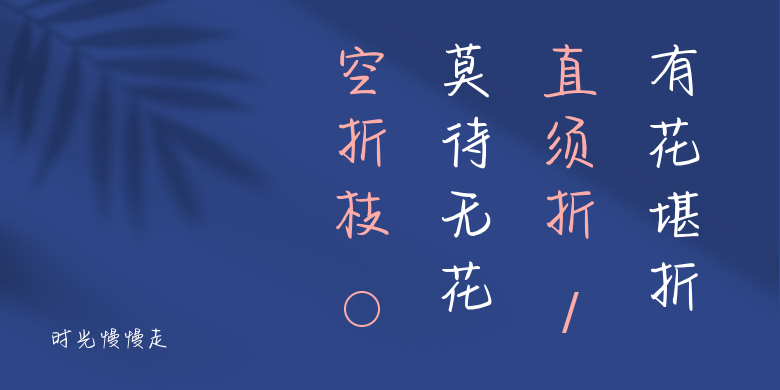
时光慢慢走
时光慢慢走,这款字体结构工整、笔画清晰,兼顾美观与易读性,适用于标题、正文、海报、包装、LOGO 等多种场景。字形优雅稳定,风格百搭耐看,适配日常排版与创意设计,让文字呈现更舒适、更具质感。时光慢慢走一笔一画,皆是细节,以均衡的比例、流畅的线条打造舒适视觉体验,字形端正大气,风格简约现代。无论是商业设计、品牌宣传还是日常排版,都能轻松驾驭,让文字更有格调与力量。时光慢慢走字体下载。